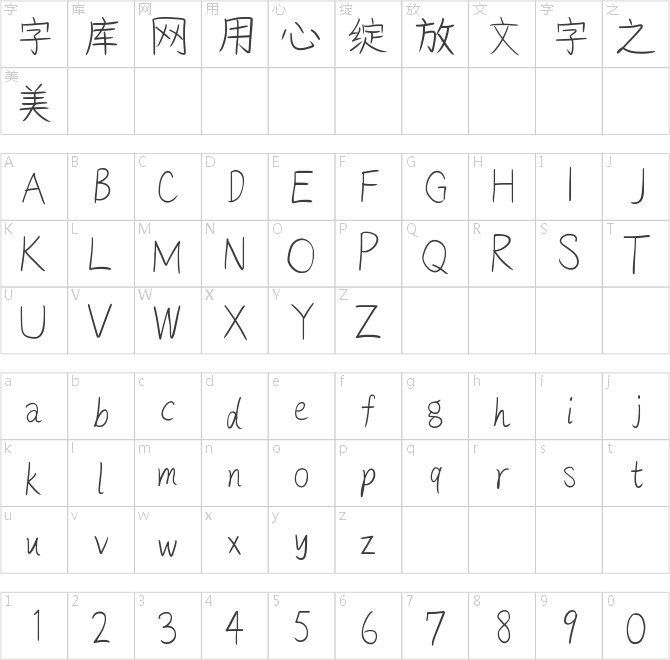
字體名稱: Acy手寫體
Acy手寫體
Acy手寫體介紹
這一款手寫體是我們國內設計師 lxfly2000 做的一款字體,他是在B站做FontForge視頻教學時放出的這一款字體
Acy手寫體字體Acy字庫是一款讓人賞心悅目、百看不厭的中文字體,適合各類廣告和產(chǎn)品包裝設計應用,字體大小5.49MB,格式為ttf字體,上傳用戶是東方時尚,作者/版權方為lxfly2000